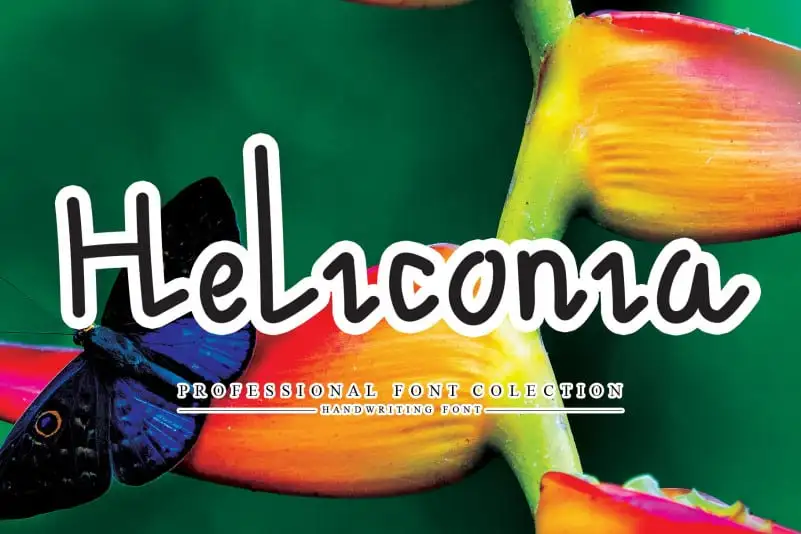
Heliconia Handwritten Font – Download Grátis
A Heliconia Handwritten Font é uma elegante escolha para aqueles que buscam um texto delicado e aconchegante. Especialmente adequada para aplicações onde o estilo de escrita criativa se destaca, como postais, embalagens de produto, identidades visuais e até mesmo na criação de logotipos para redes sociais. Suas linhas suaves e detalhes delicados são ideais para personalizar produtos finos ou trabalhos artísticos, proporcionando um toque especial em qualquer tipo de material. Esta fonte é perfeita tanto para o design gráfico quanto para a decoração, garantindo que sua mensagem seja transmitida com sofisticação e elegância. Com sua versatilidade ampla, é uma ótima opção para quem busca adicionar um toque único em qualquer projeto visual.